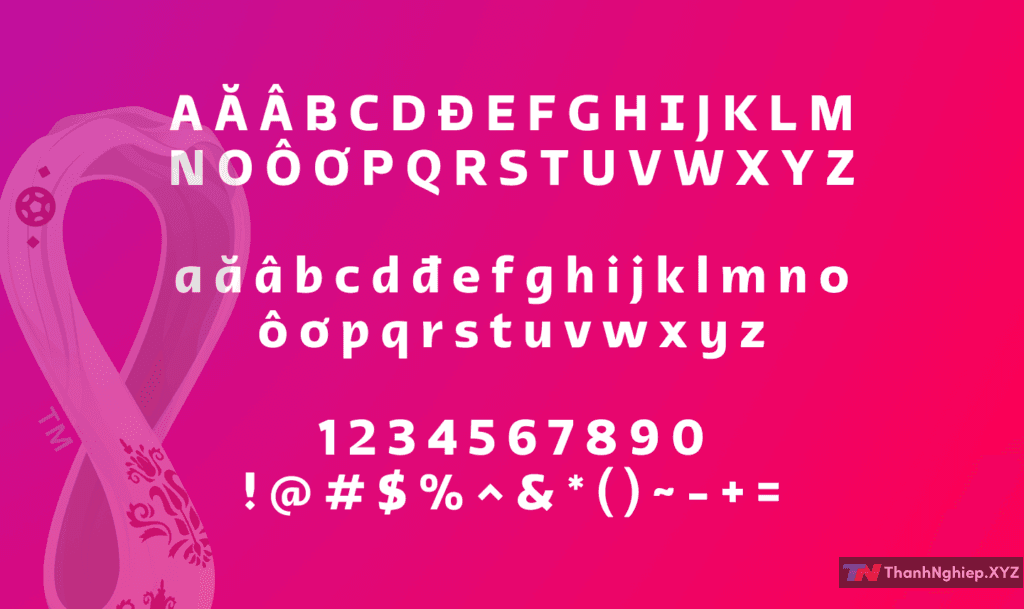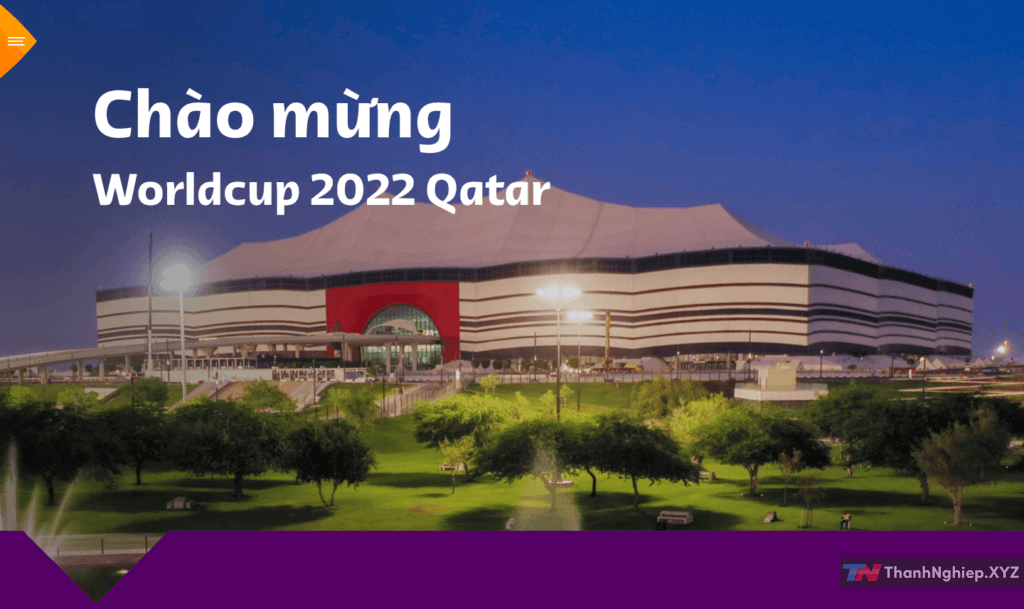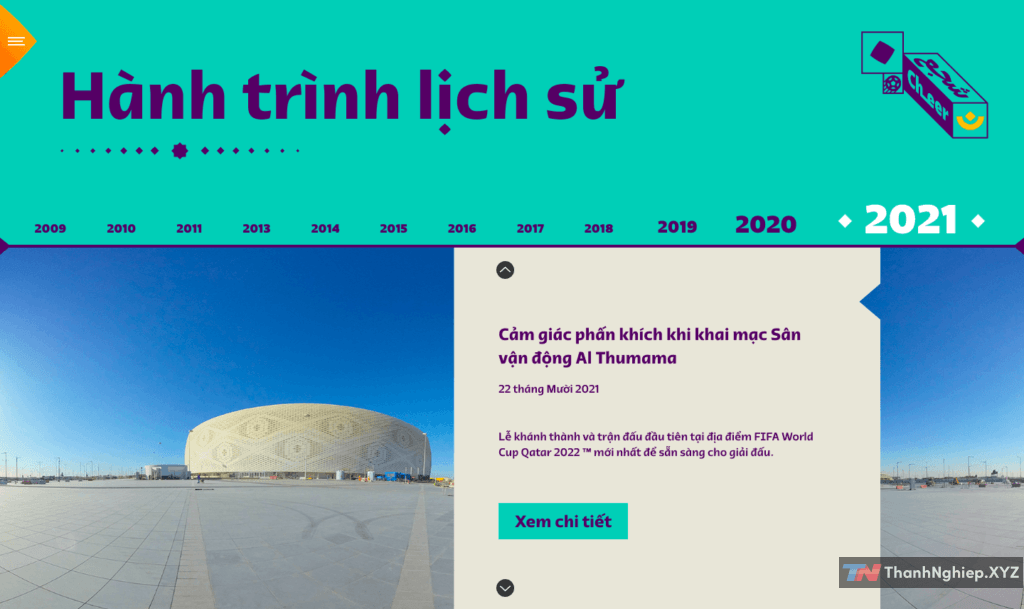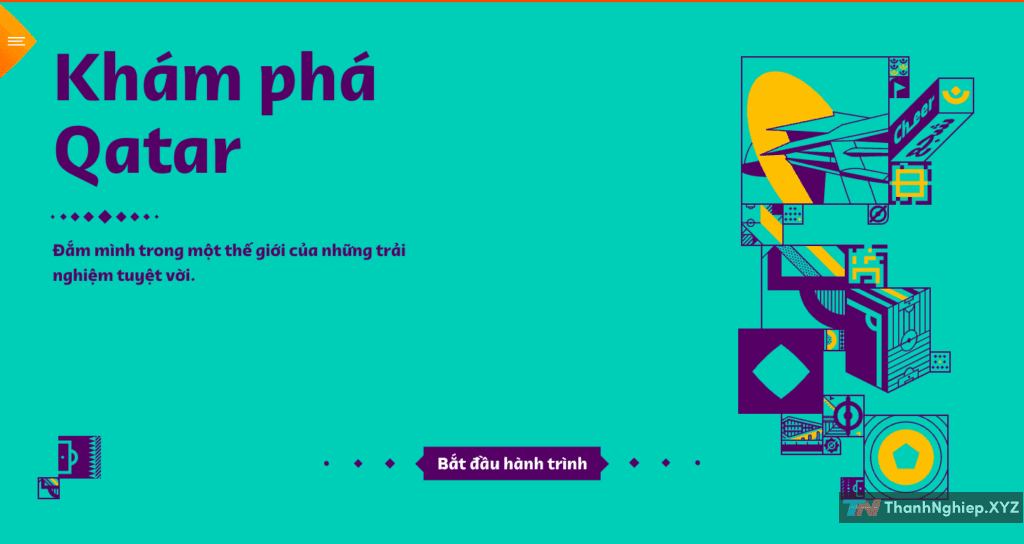
Font TVN-Qatar World Cup 2022 Việt Hóa, là font nhận diện thương hiệu của Giải bóng đá World Cup 2022 được tổ chức tại Qatar từ ngày 20 tháng 11 đến 18 tháng 12 năm 2022.
Font này được sử dụng trên tất cả ấn phẩm thương mại và sản phẩm của World Cup như Website, banner, áo, túi, billboard, hình ảnh trên truyền hình, visual image…
Bộ font chữ TVN-Qatar World Cup 2022 với các nét đều nhau, nhìn hài hòa và năng động. Đơn giản vì nó đẹp, đường nét của font chữ phóng khoáng mang phong cách ả rập, các chữ cái gần nhau nhưng không tạo cảm giác “rối rít tít mù”.
Việt hoá từ Font Qatar-2022, bởi TienTH
Tên font: TVN-Qatar2022
Bộ font gồm có 3 style:
- TVN-Qatar2022 – Medium
- TVN-Qatar2022 – Bold
- TVN-Qatar2022 – Heavy